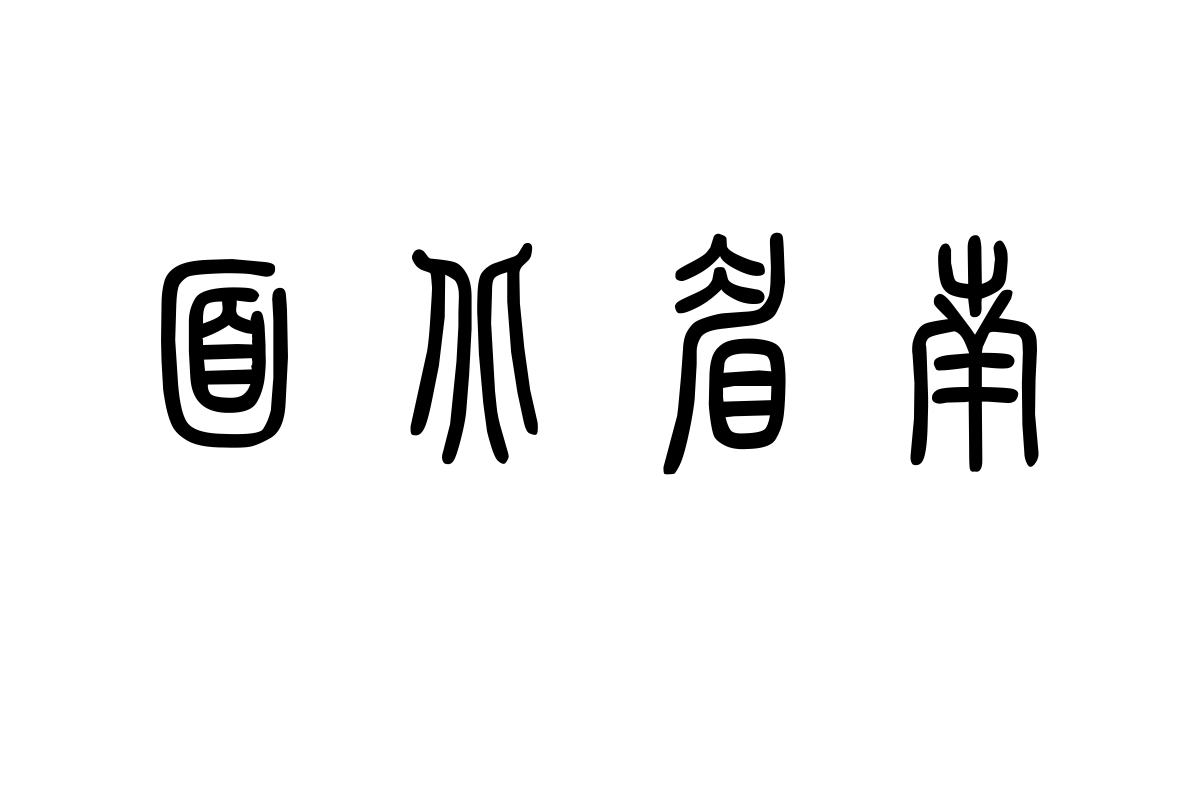
汉仪粗篆繁字体是一套由汉仪公司设计开发的中文字体,主要用于网页、印刷品等需要展示汉字的场合。该字体的特点是笔画粗壮有力,结构紧凑,具有很高的辨识度和美观度。
汉仪粗篆繁字体的特点如下:
1. 笔画粗壮有力:该字体的笔画粗细适中,线条饱满有力,给人一种强烈的视觉冲击感。
2. 结构紧凑:该字体的结构紧凑,每个字的笔画都紧密相连,没有多余的空间,使得整个字体看起来更加整洁有序。
3. 辨识度高:由于笔画粗壮有力,该字体在各种场合下都能很好地识别,尤其是手写体和印刷体。
4. 美观度高:该字体在保持笔画粗壮有力的同时,还注重整体的美感,使得整个字体看起来既庄重又不失活泼。
5. 适用范围广泛:该字体适用于各种场合,如网页设计、印刷品制作、广告设计等,具有较高的实用价值。